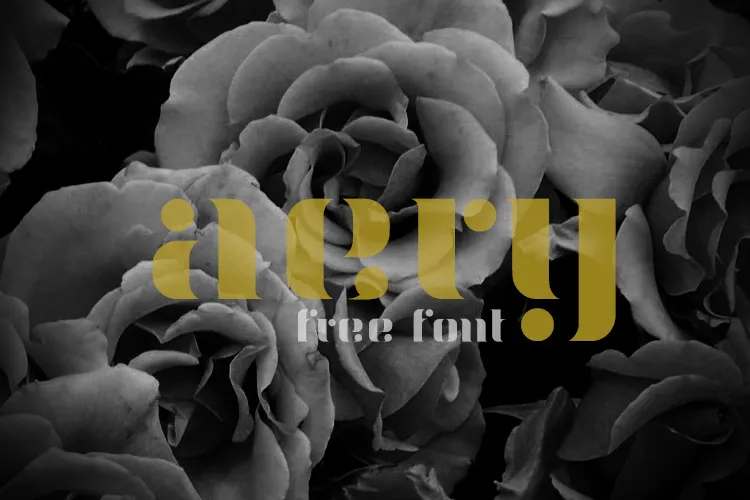
AERY Font é uma fonte display inspirada no Bodoni criada por Hamilton, com nuances que lembram a elegância e glamour do tipo de texto deste estilo clássico. Esta fonte está disponível como uma opção poderosa para quem deseja dar um toque chic e único às suas criações digitais. Inspirado pela robusta beleza dos Bodoni, AERY apresenta uma face em minúsculas que é tanto um ato de declaração quanto uma forma de expressar o charme natural de quem a usa. Ideal para gráficos de marca ou materiais publicitários de alto nível, esta fonte transmite confiança sem esforço. AERY traz consigo um peso significativo de encanto que não precisa provar nada além da sua própria presença irresistível. É perfeita para os designers em busca de uma mão na massa que ressalta a estética e o estilo de seus trabalhos, sem precisar explicar ou justificar seu uso.